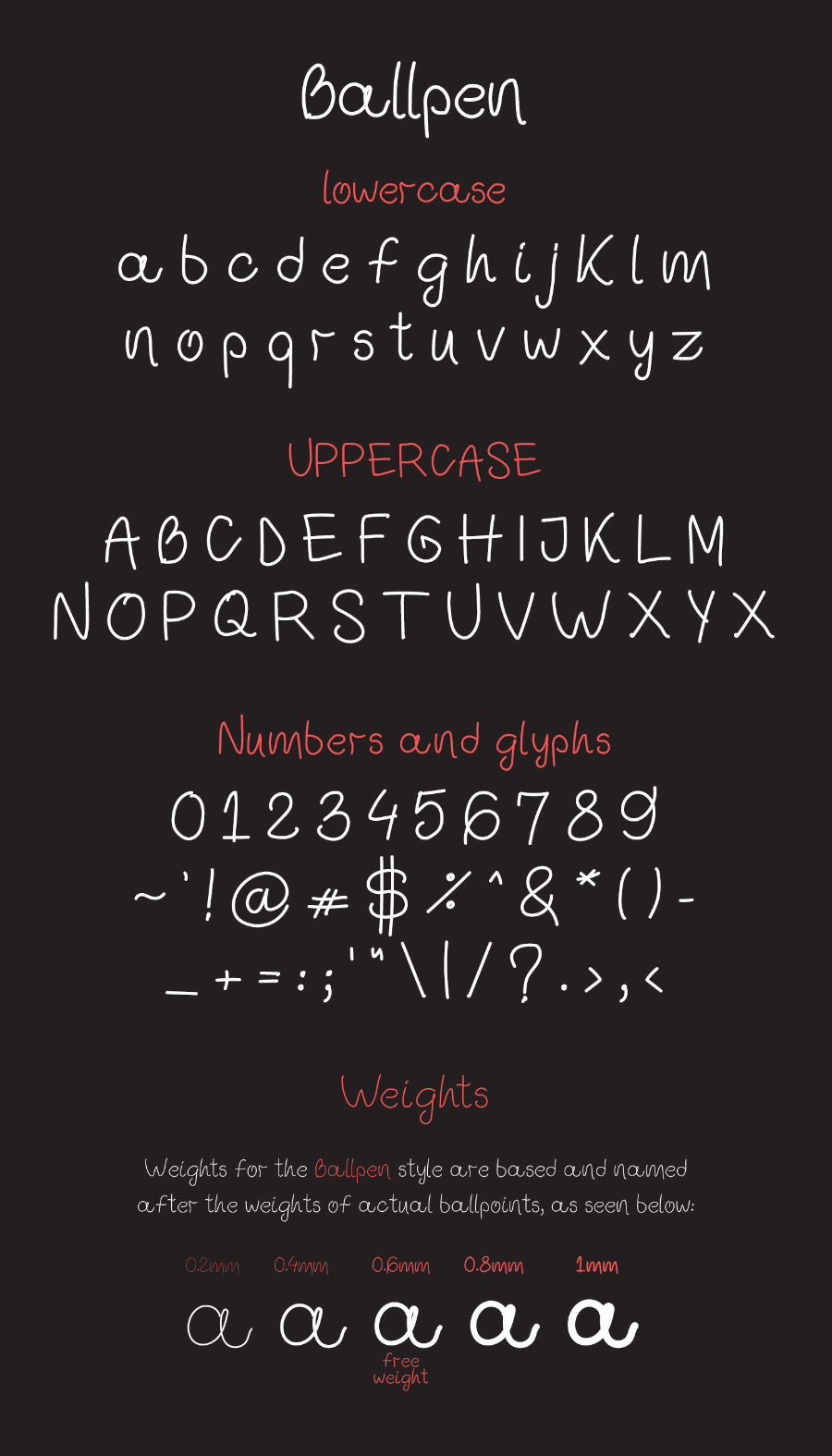
圆珠笔免费演示字体
满足圆珠笔免费演示字体,两种风格的手写字体:圆珠笔和粉笔。完整的字体系列提供了6种字体,一种是粉笔风格,另一种是Ballpen的5种字体。圆珠笔的重量是根据实际的笔重命名的,它们是:0.2mm,0.4mm,0.6mm,0.8mm和1mm。您来这里下载的自由重量是0.6毫米,您可以将其用于个人和商业项目。另外,整个字体都带有基本的英文字母和数字。此外,还提供了基本的标点符号和字形,如上所述。